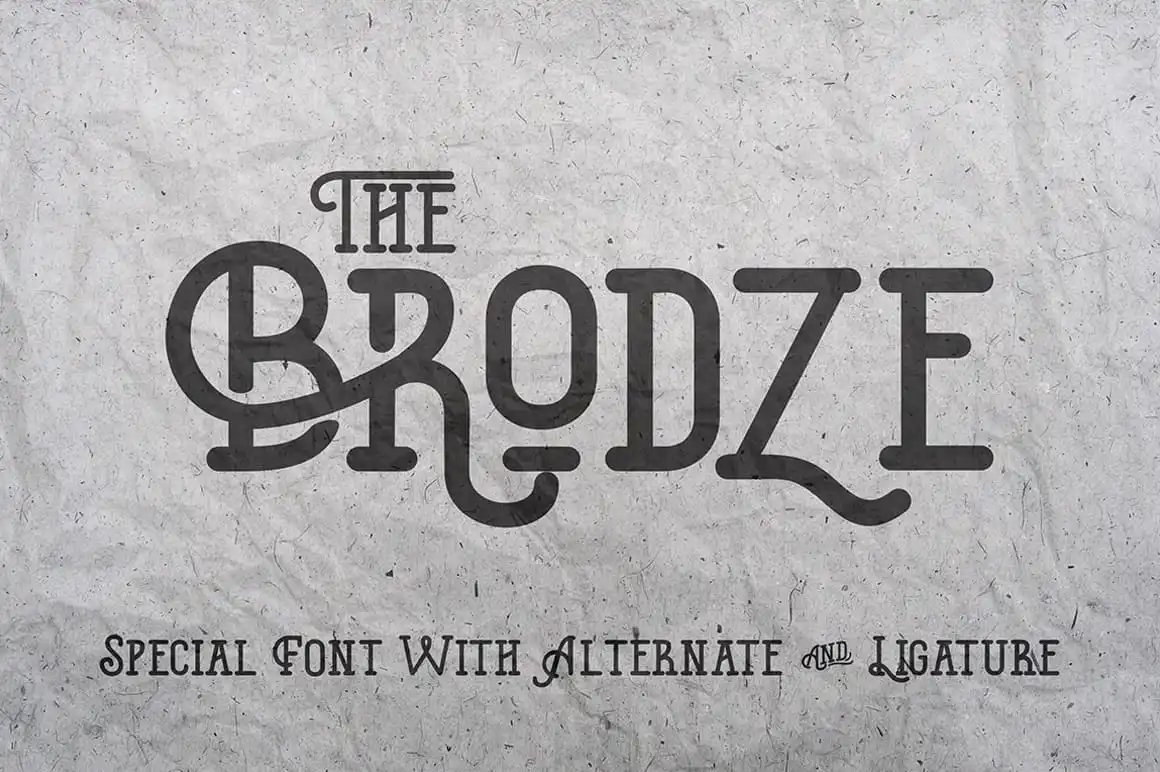
The Brodze Typeface – Download Grátis
Agora temos The Brodze Typeface, uma tipografia exclusiva com alternativas e ligatura que traz a sensação de flexibilidade do seu próprio estilo pessoal. Com um design refinado e adaptável para diversos tipos de aplicação, este tipo é perfeito para criar cartões de convite, estilizar marcas ou simplesmente sobrepor texto a imagens de fundo de qualquer tipo. Inspirado em uma personalidade única, The Brodze apresenta-se como a escolha certa para aqueles que buscam um toque diferente e criativo no design visual. Uma fonte moderna e versátil, o Brodze traz novos recursos à sua biblioteca de tipografias, revitalizando as possibilidades do seu próximo projeto.